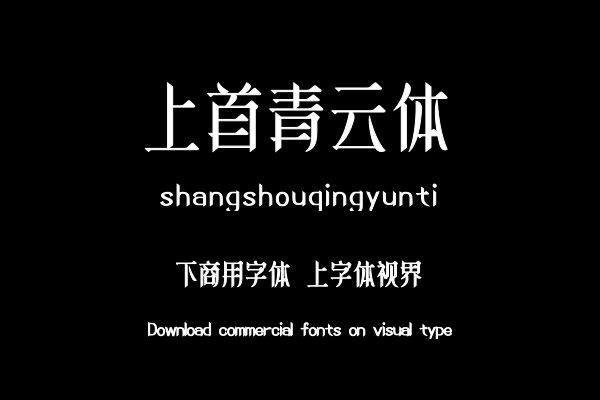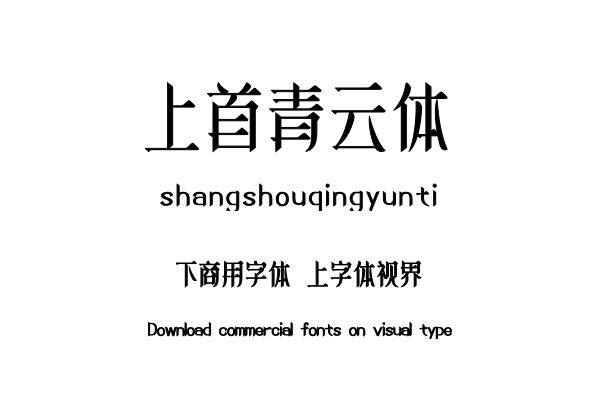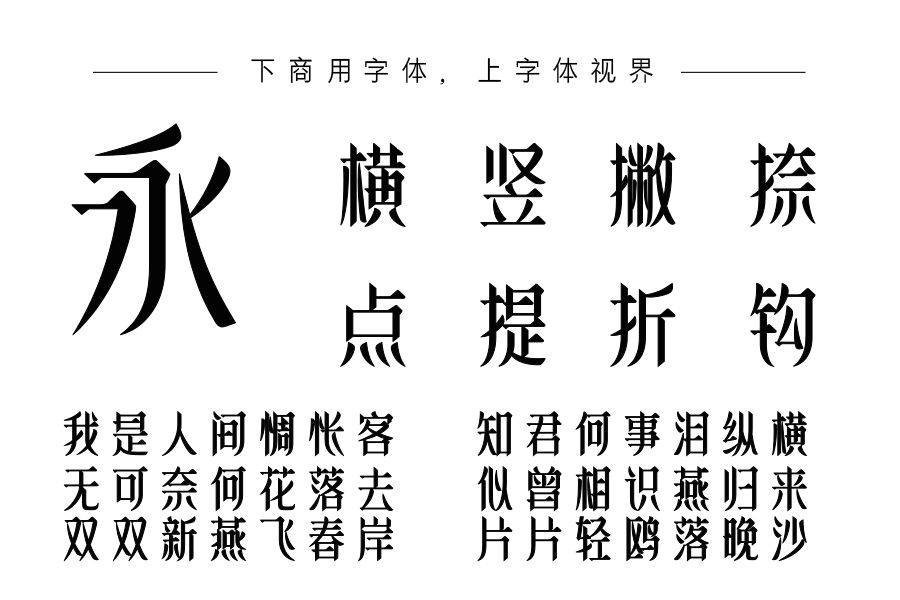
上首青云体其笔画横平竖直,却又刚中带柔,整体字形规范、简洁的同时也蕴含着一股肆意潇洒的气息。碧波江上,一叶孤舟,岸边柳枝随风飘起,在那连绵山峰之间,一轮朝阳冉冉......购买须知:“下载服务费”与“字体VIP”所获得字体 仅用于个人非商用, 商用请联系付费授权。本字体为电脑用字,手机没有root权限不支持直接手机换字(手机如何root,请自行百度搜索教程)。购买前请先 了解清楚后再付款 ,字体为虚拟产品无法回收 一旦购买不支持退款。